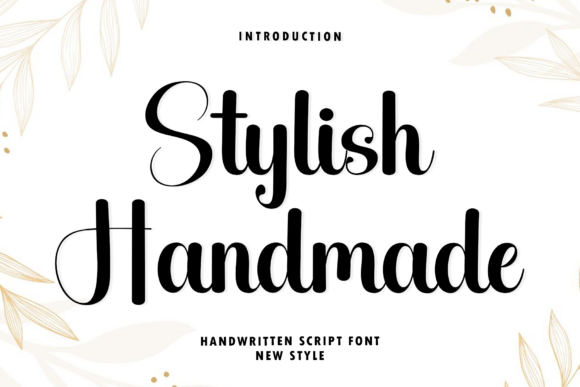
Stylish Handmade
Stylish Handmade – La police manuscrite qui réinvente l’élégance moderne
Vous cherchez une typographie qui allie raffinement et modernité pour vos projets premium ? Stylish Handmade est la réponse. Cette police handwritten au style « new style » se démarque par son mouvement fluide, proche d’une signature authentique, et séduit immédiatement les marques de luxe, les créateurs de logos, les invitations de mariage et les publications éditoriales haut de gamme.
Pourquoi choisir Stylish Handmade pour votre identité visuelle ?
- Équilibre parfait : des ascendantes élancées et des boucles gracieuses qui offrent un rythme visuel harmonieux.
- Versatilité premium : idéale pour le branding de luxe, les logos signature, les faire‑part de mariage et les mises en page editoriales sophistiquées.
- Impact immédiat : chaque mot devient une déclaration de classe et de distinction.
Applications concrètes de Stylish Handmade
Imaginez votre logo gravé avec des traits fluides qui rappellent une signature personnelle, ou vos invitations de mariage sublimées par des lettres qui dansent sur le papier. Les magazines de mode et les catalogues de bijoux gagnent en prestige lorsqu’ils utilisent cette police pour les titres et les citations clés.
Conclusion
Si vous désirez injecter une dose d’élégance intemporelle dans vos créations, Stylish Handmade est la police incontournable. Son équilibre subtil entre style moderne et douceur manuscrite transforme chaque texte en une véritable œuvre d’art, tout en renforçant votre brand identity et votre visibilité en ligne.